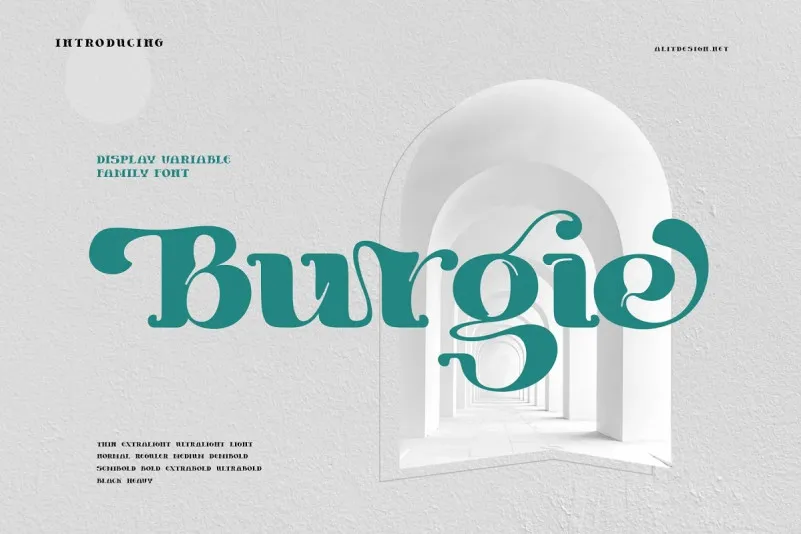
Burgie Black Serif Font – Fonte Grátis
Burgie Black Serif Font
A Burgie Black Serif Font é uma elegante serif que traz ao seu design um toque de versatilidade e originalidade. Criada pelo alit design, essa fonte apresenta alternativas de swash e estilo único, característica perfeita para se destacar em projetos gráficos tradicionais, designs retro ou até mesmo em outdoors. O resultado é uma família de fontes que vai desde os traços mais finos até aqueles mais robustos, tornando sua marca distintiva e única no mercado. Perfeito tanto para ambientes clássicos quanto para um design moderno, a Burgie Black Serif é uma ótima escolha para designers buscando personalidade em seus projetos visuais.